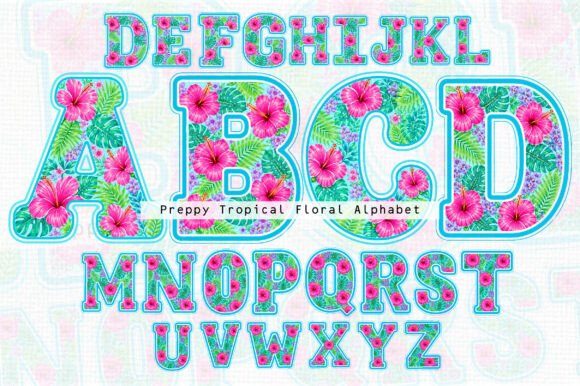
Preppy Tropical Floral Alphabet Bundle
Việc tìm kiếm các thành phần thiết kế phù hợp có thể là một thách thức, nhưng Preppy Tropical Floral Alphabet Bundle cung cấp một bộ sưu tập đặc biệt giúp nâng tầm công việc của bạn ngay lập tức.
Cho dù bạn đang tạo sản phẩm POD (In theo yêu cầu), thiệp mời đám cưới hay đồ họa mạng xã hội, Preppy Tropical Floral Alphabet Bundle đều là một sự lựa chọn lý tưởng.